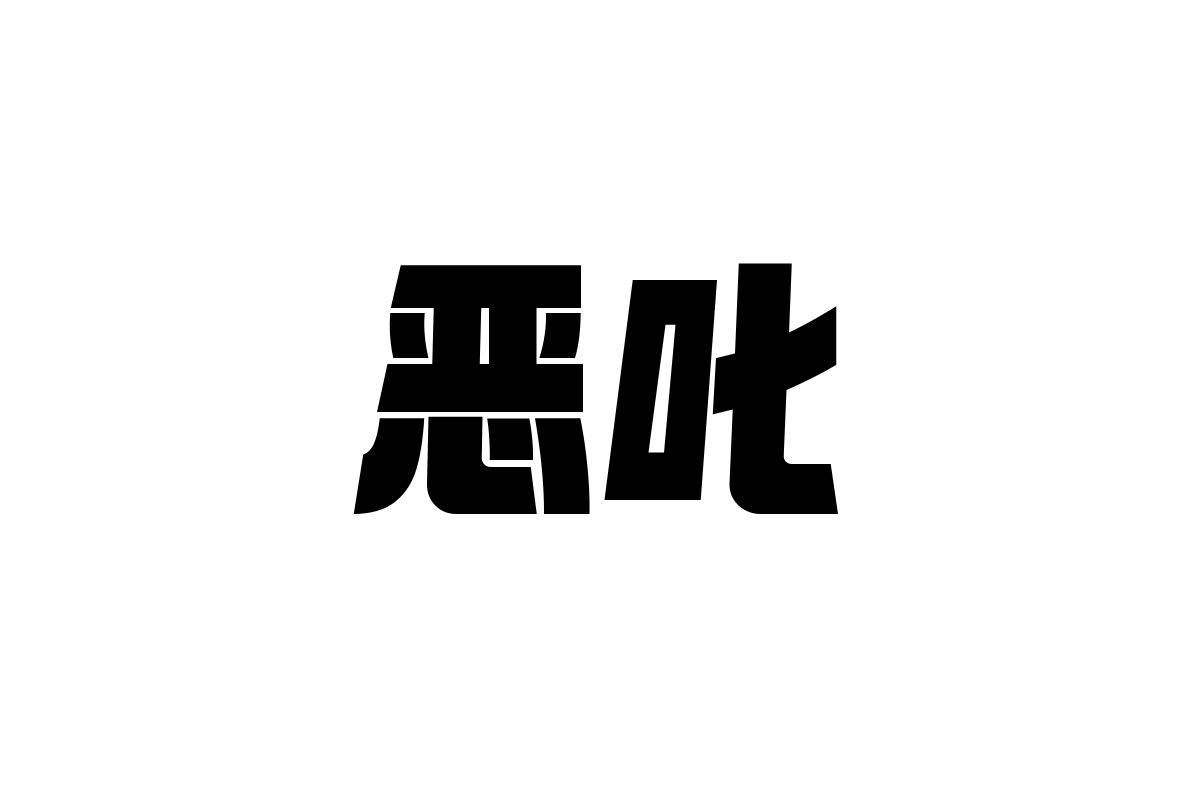
锐字太空筑梦黑超黑是一款独特的字体,它以太空为主题,给人一种神秘、科幻的感觉。这款字体的特点是笔画粗细不一,线条流畅,有一种科技感和未来感。它的字形结构独特,线条弯曲,给人一种立体的感觉。
锐字太空筑梦黑超黑适用于需要表现科幻、科技、未来等主题的场合,如科幻小说、游戏、广告、海报等。它能够很好地传达出一种神秘、科幻的氛围,让人仿佛置身于一个充满未知和探索的世界。